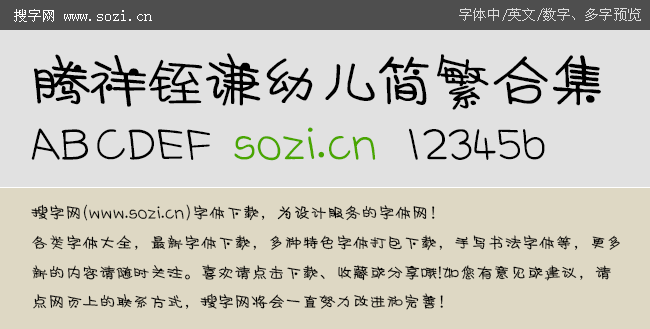
騰祥铚謙幼兒簡(jiǎn)繁合集
搜字網(wǎng)提供一款騰祥铚謙幼兒簡(jiǎn)繁合集中文藝術(shù)字體下載,騰祥铚謙幼兒字體是一款手寫風(fēng)格的卡通字體,字體天真可愛,充滿童趣。 可用于出版印刷、廣告設(shè)計(jì) 網(wǎng)頁(yè)設(shè)計(jì)、包裝設(shè)計(jì)、屏幕顯示等領(lǐng)域。